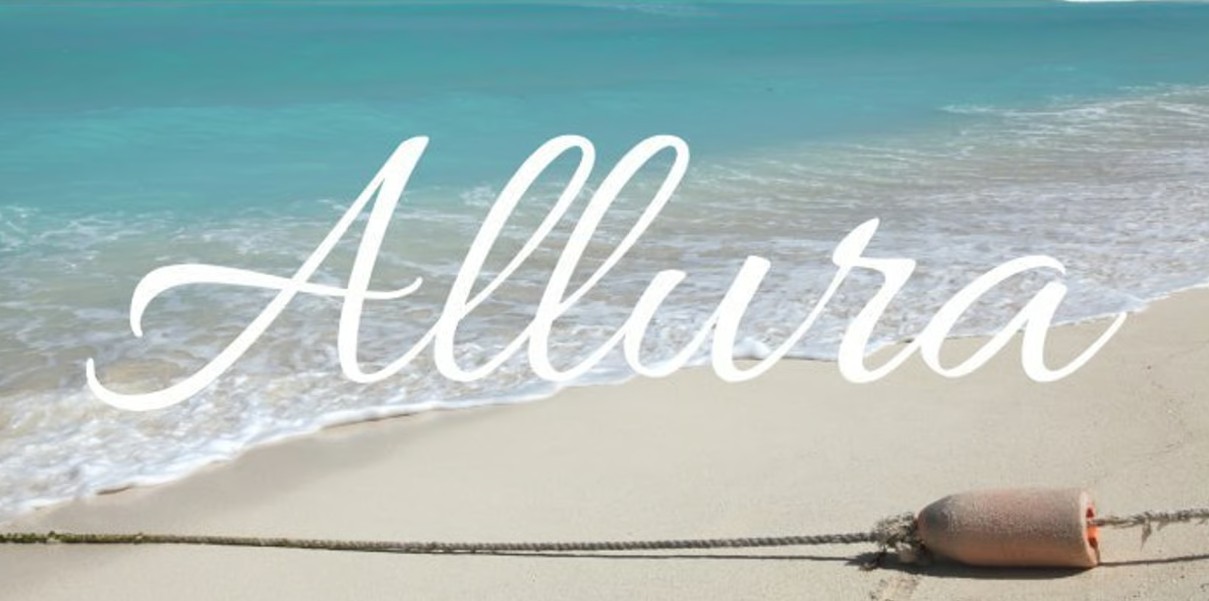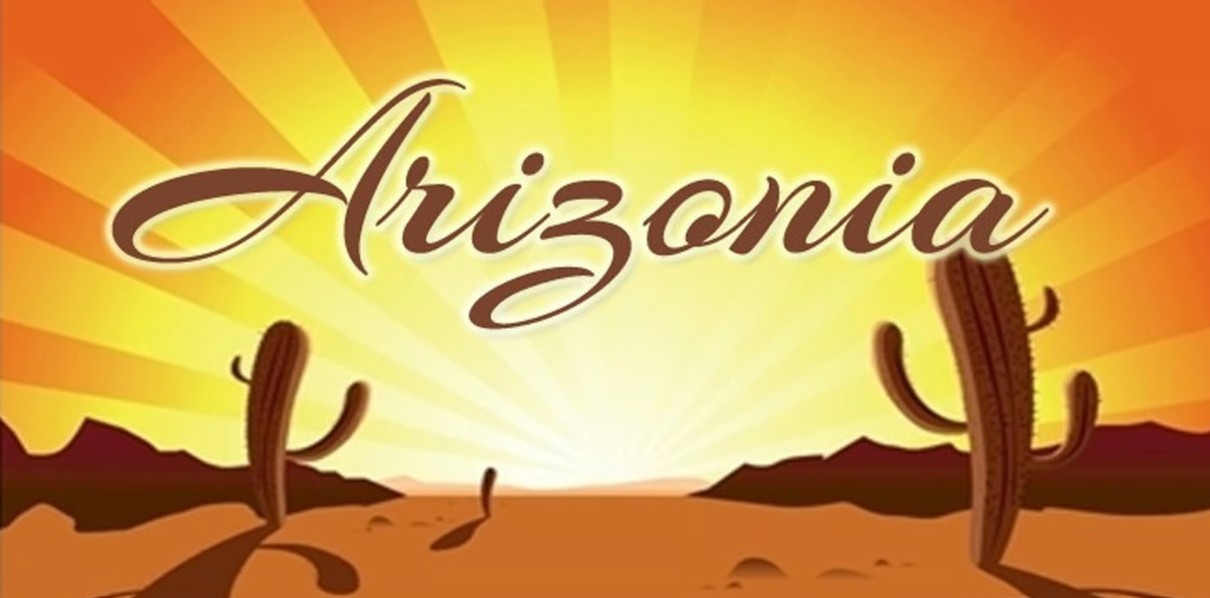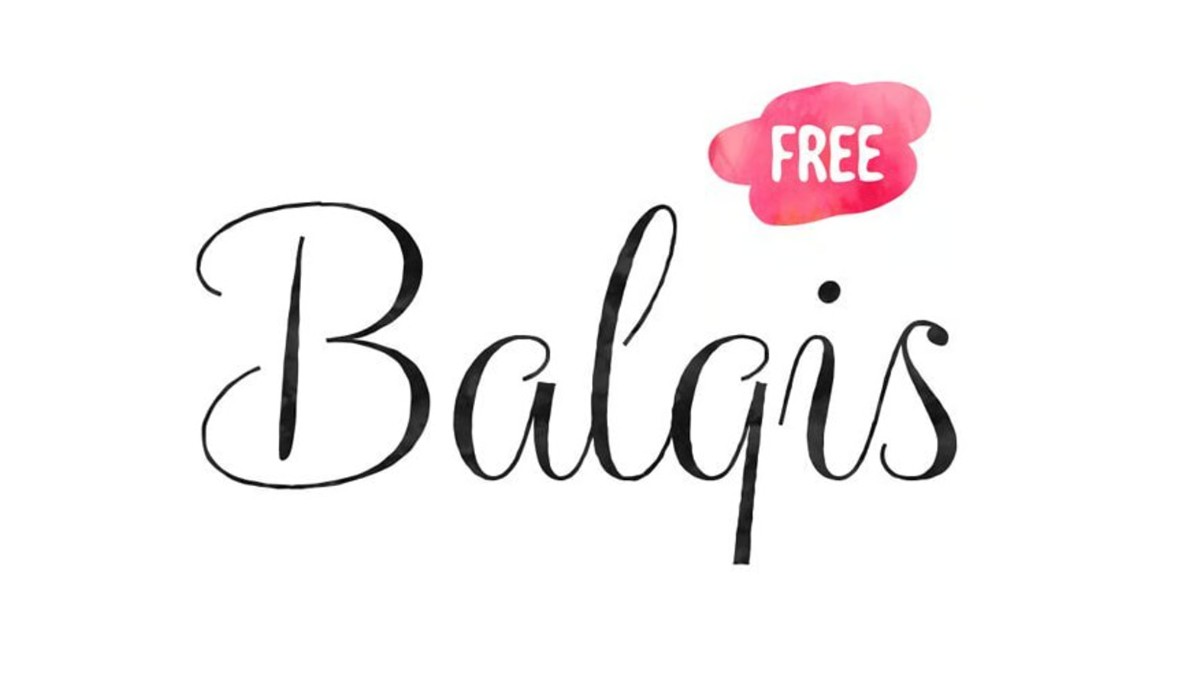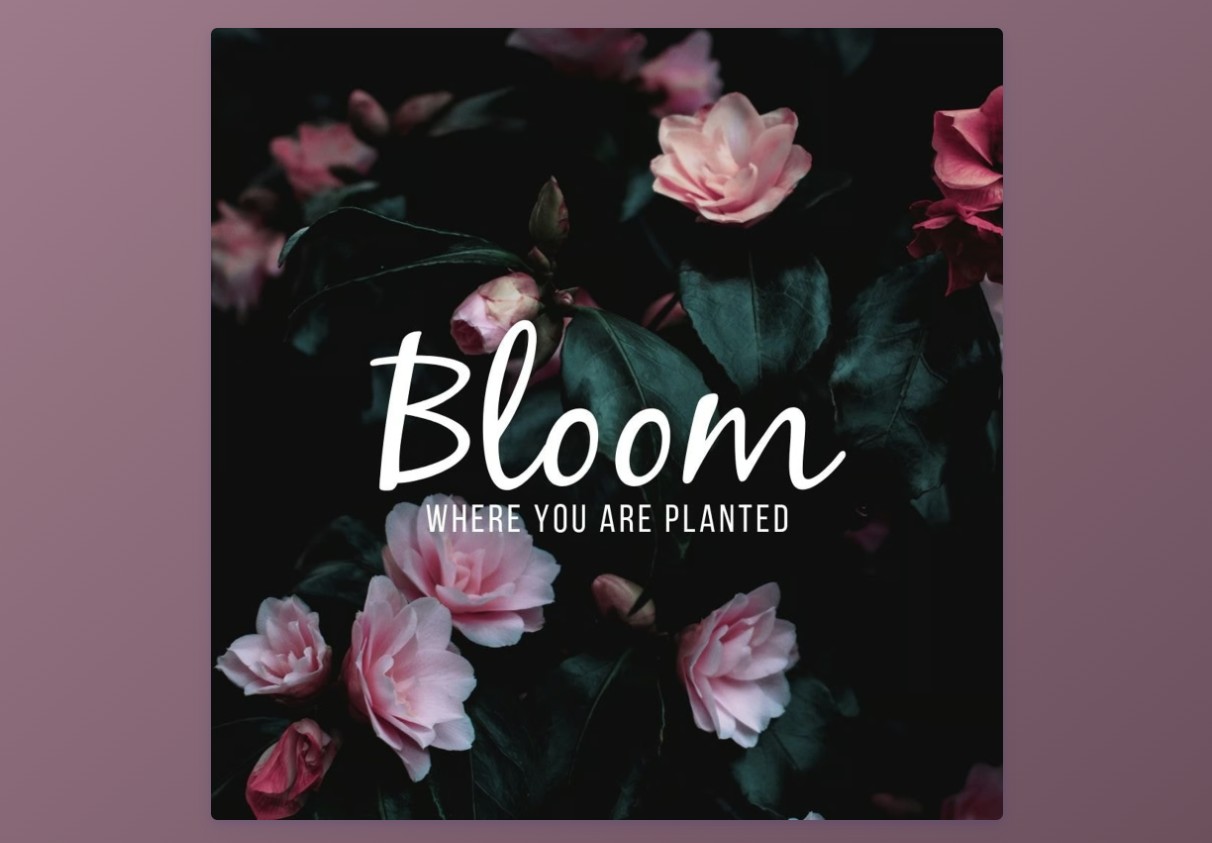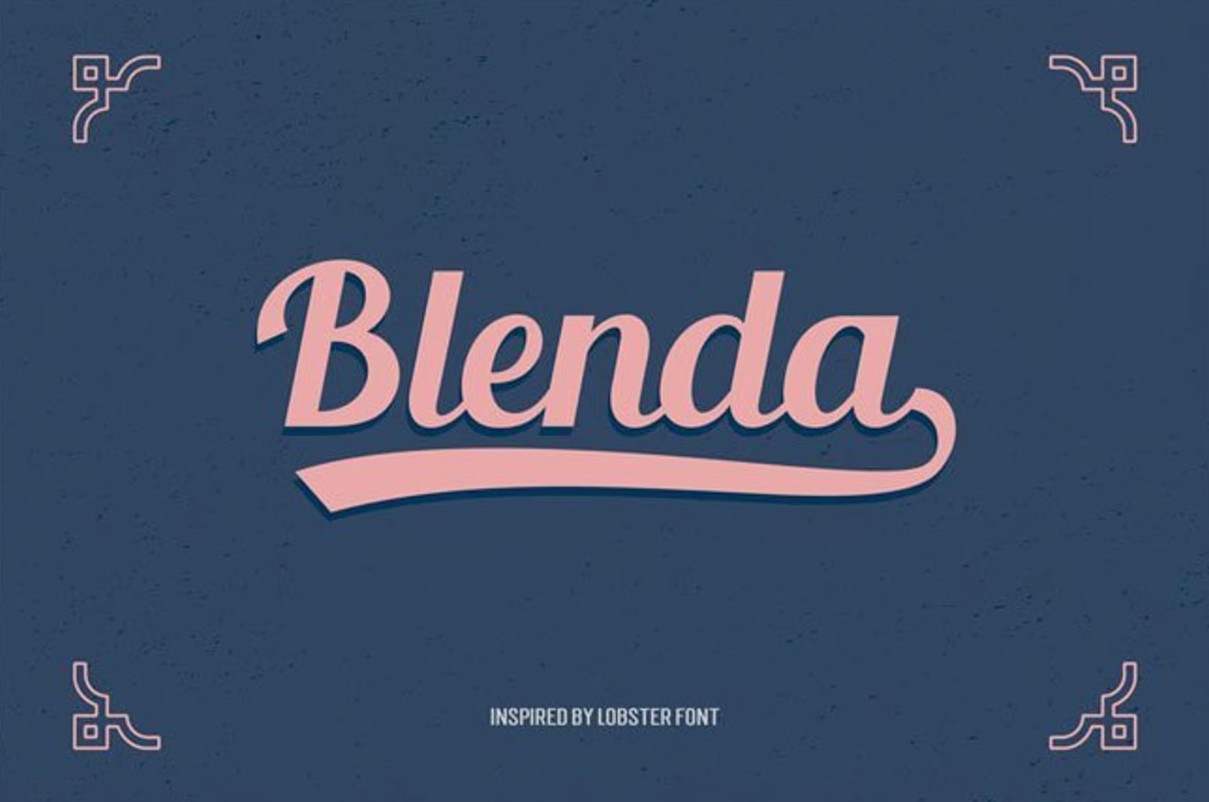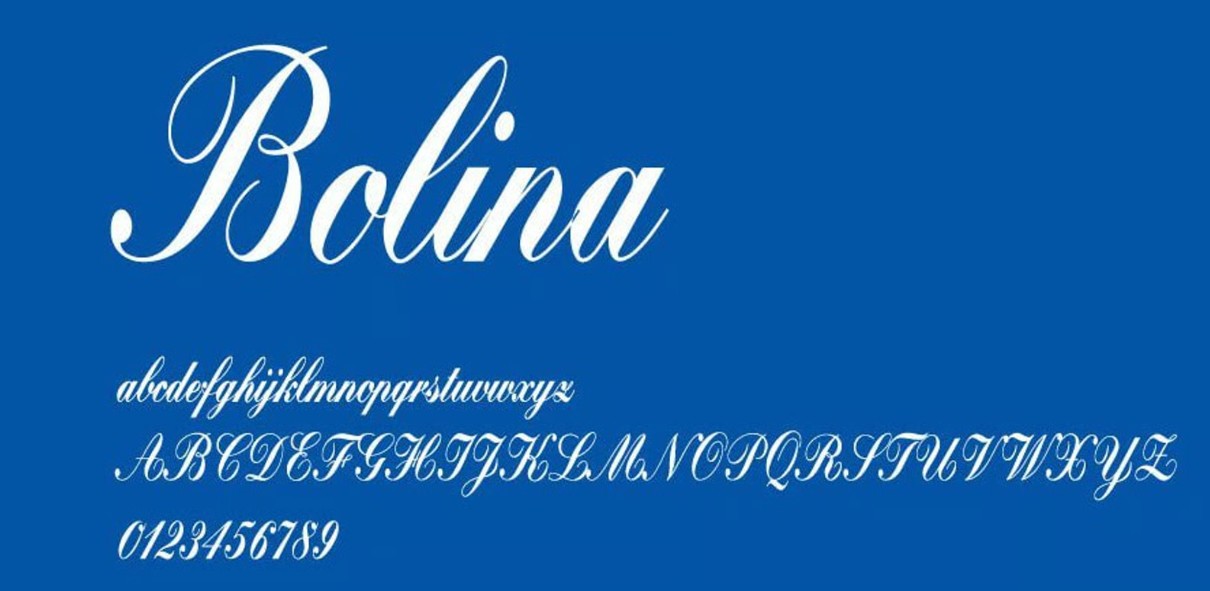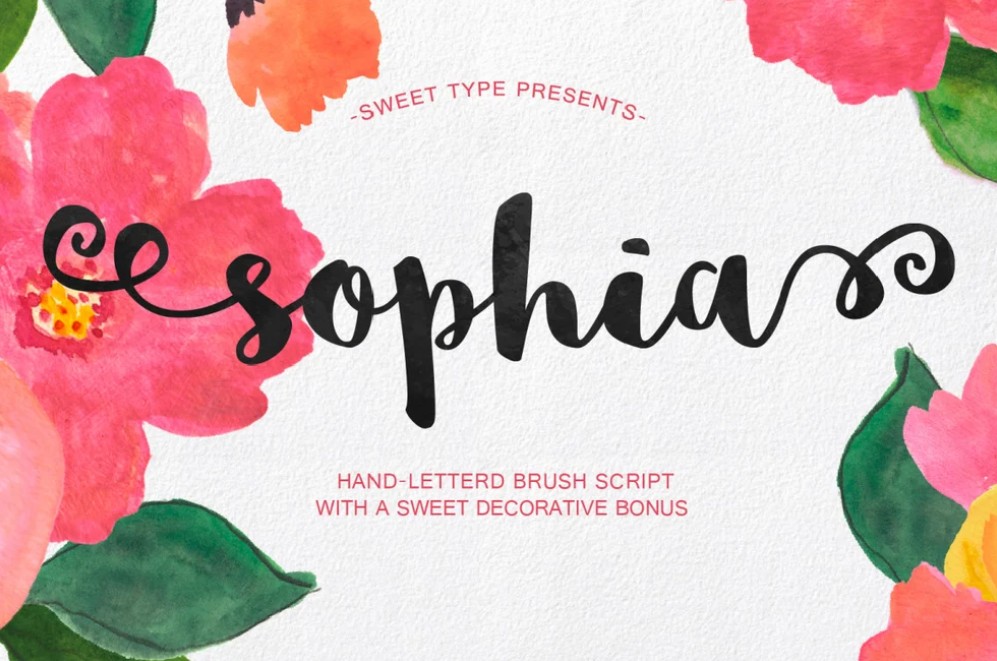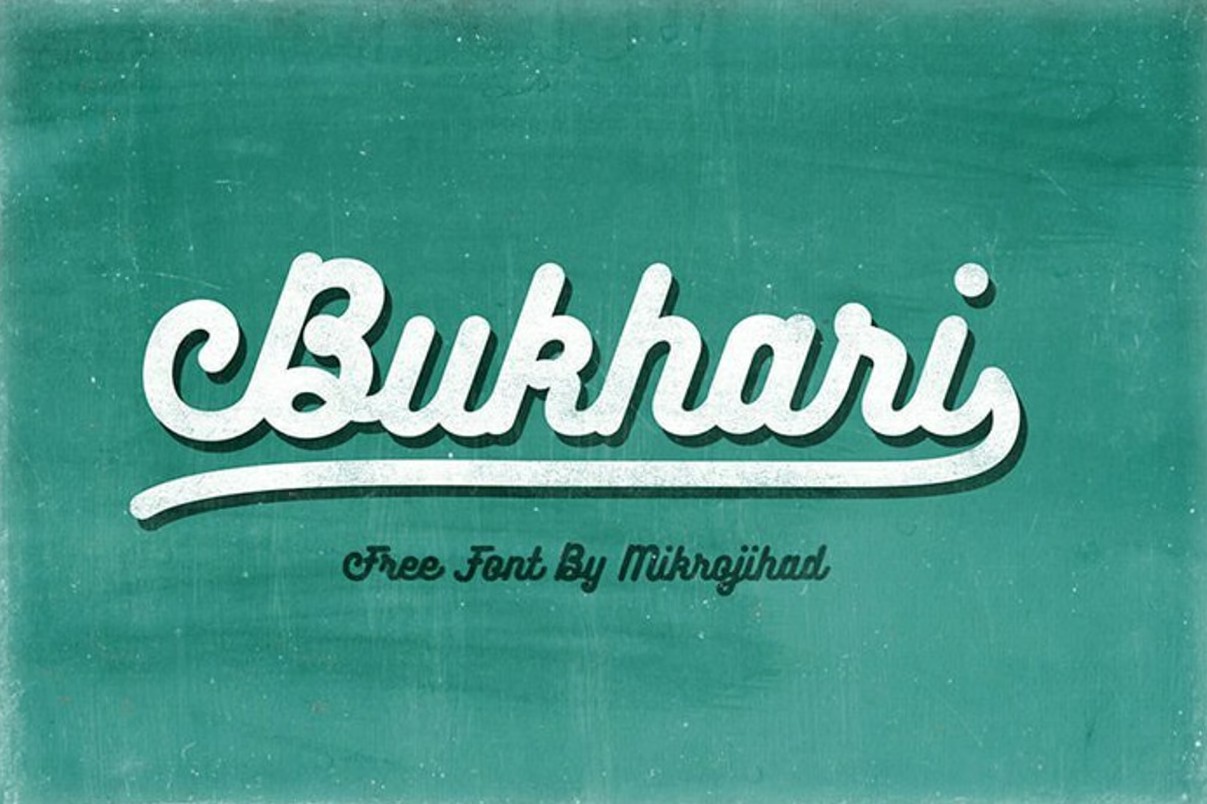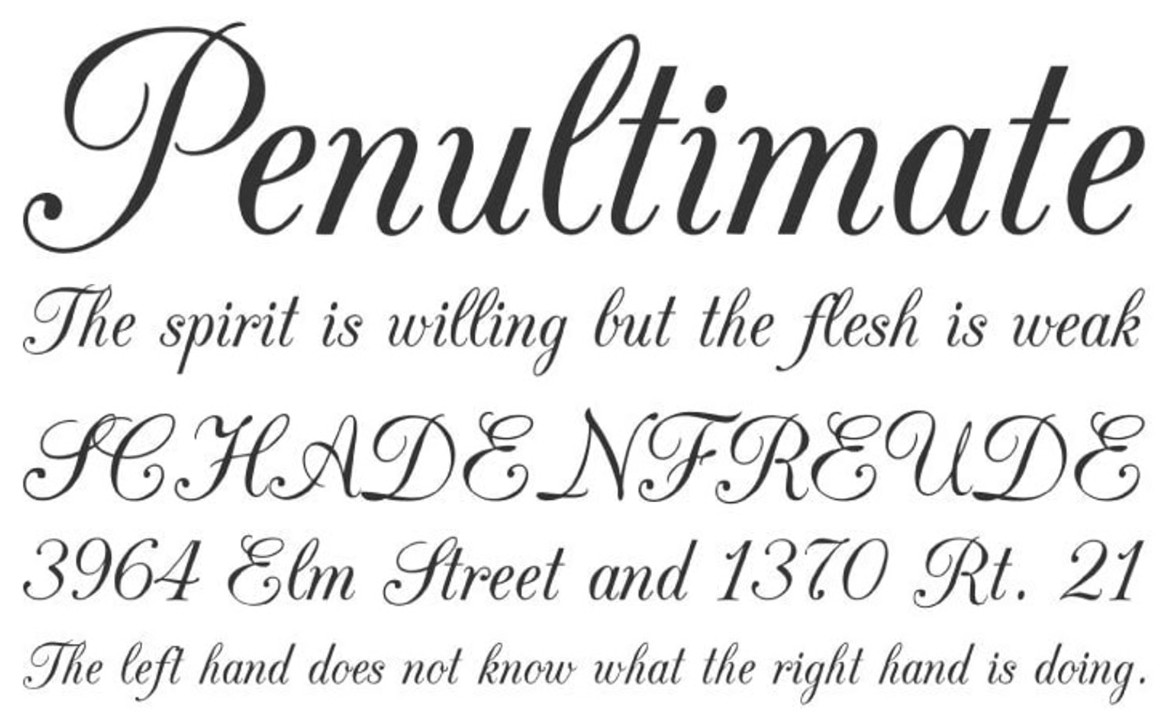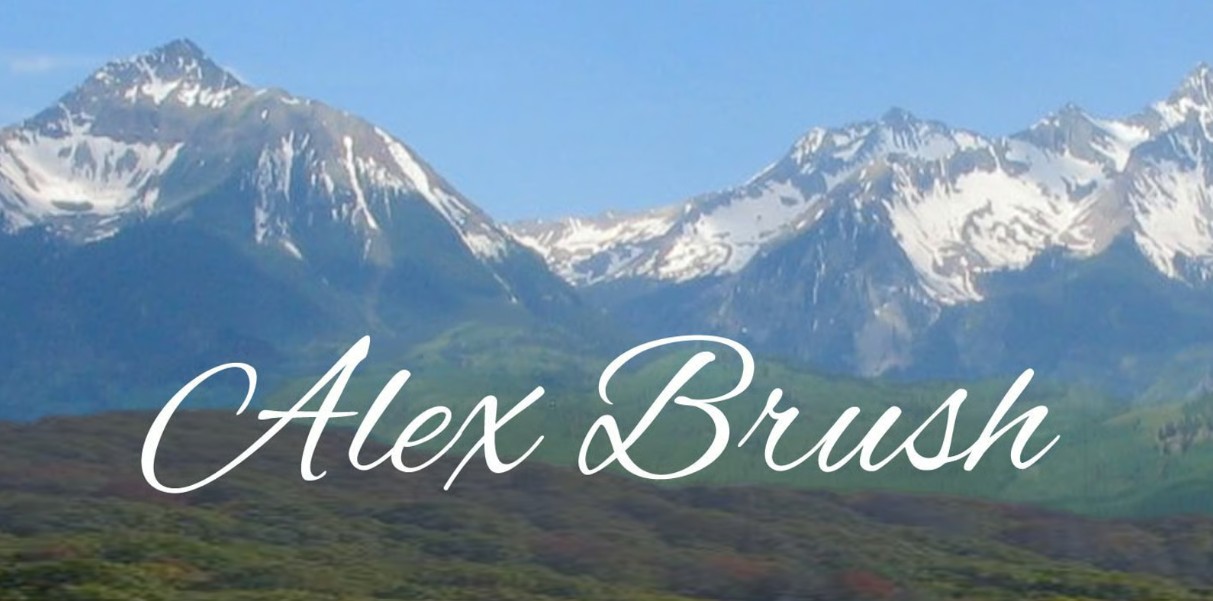
Top 10 font chữ viết tay đẹp miễn phí
Font chữ viết tay luôn là lựa chọn được nhiều nhà thiết kế yêu thích nhờ khả năng tạo cảm giác tự nhiên, cá nhân và giàu cảm xúc.
Top 10 font chữ viết tay đẹp miễn phí
Phông chữ viết tay (handwritten font) luôn là một trong những lựa chọn được yêu thích trong thiết kế đồ họa nhờ khả năng tạo cảm giác gần gũi, cá nhân và giàu cảm xúc. Khác với các kiểu chữ máy tính truyền thống, font chữ viết tay mô phỏng nét chữ tự nhiên của con người, mang đến sự mềm mại, độc đáo và giúp các sản phẩm thiết kế trở nên nổi bật hơn.
Trong nhiều lĩnh vực như thiết kế logo, bao bì sản phẩm, thiệp mời, poster, bài đăng mạng xã hội hay nhận diện thương hiệu, phông chữ viết tay thường được sử dụng để tạo điểm nhấn và truyền tải phong cách riêng. Tùy theo đặc điểm từng loại font, người thiết kế có thể lựa chọn kiểu chữ thanh lịch, cổ điển, trẻ trung hoặc cá tính.
Hiện nay có rất nhiều phông chữ viết tay miễn phí được chia sẻ dành cho mục đích cá nhân và một số dự án thương mại. Trong đó, 10 font chữ như Alex Brush, Allura Regular, Arizonia, Balqis, Black Jack, Blenda, Bolina, Sophia, Bukhari Script và CAC Champagne là những lựa chọn nổi bật nhờ thiết kế đẹp mắt, dễ sử dụng và phù hợp với nhiều phong cách sáng tạo khác nhau.
1. Alex Brush
Alex Brush là một phông chữ viết tay mang phong cách thư pháp cổ điển với những nét cọ mềm mại và phần chữ hoa đầy ấn tượng. Đây là kiểu font được thiết kế theo hướng thanh lịch, tạo cảm giác sang trọng nhưng vẫn giữ được sự tự nhiên của nét viết tay.
Điểm đặc biệt của Alex Brush nằm ở phần nét chữ không quá dài ở các ký tự lên cao và xuống thấp như nhiều font thư pháp khác. Điều này giúp font trở nên dễ đọc hơn, ngay cả khi được sử dụng trong các đoạn chữ dài hoặc kích thước nhỏ.
Với vẻ đẹp cổ điển và khả năng hiển thị rõ ràng, Alex Brush phù hợp cho nhiều thiết kế như logo thương hiệu cao cấp, thiệp cưới, tiêu đề sách, poster nghệ thuật hoặc các sản phẩm yêu cầu sự tinh tế. Đây là một lựa chọn lý tưởng dành cho những ai muốn tạo cảm giác sang trọng nhưng không quá cầu kỳ.
2. Allura Regular
Allura Regular là một font chữ viết tay mang phong cách nhẹ nhàng, bay bổng với cảm giác tự nhiên giống như nét chữ được viết bằng tay. Font này nổi bật bởi các đường cong mềm mại, tạo nên vẻ đẹp nữ tính và thanh lịch.
Không giống nhiều font thư pháp phức tạp, Allura Regular có thiết kế đơn giản, dễ đọc và có tính ứng dụng cao. Nhờ sự cân bằng giữa nét trang trí và khả năng hiển thị, font chữ này có thể sử dụng trong nhiều loại dự án khác nhau.
Allura Regular đặc biệt phù hợp với thiết kế bao bì sản phẩm, thương hiệu mỹ phẩm, thiệp chúc mừng, logo cá nhân hoặc các nội dung cần tạo cảm giác thân thiện. Sự linh hoạt của font giúp nó trở thành một trong những lựa chọn phổ biến trong nhóm font viết tay miễn phí.
3. Arizonia
Arizonia là một phông chữ viết tay gây chú ý nhờ sự kết hợp giữa các nét đậm và nét mảnh thay đổi linh hoạt. Sự tương phản này tạo nên cảm giác chuyển động, giúp chữ viết trở nên nổi bật và có chiều sâu hơn.
Font Arizonia sở hữu nhiều ký tự đặc biệt, trong đó một số chữ thường như ký tự “z” được thiết kế rất độc đáo. Ngoài ra, font còn mang một chút ảnh hưởng từ phong cách chữ Ả Rập, tạo nên nét riêng biệt so với các font thư pháp thông thường.
Với vẻ ngoài cá tính và giàu tính nghệ thuật, Arizonia thích hợp cho tiêu đề lớn, poster, thiết kế thời trang, bìa album hoặc các dự án cần tạo ấn tượng mạnh ngay từ cái nhìn đầu tiên.
4. Balqis
Balqis là font chữ viết tay hiện đại với phong cách đơn giản, nhẹ nhàng và gần gũi. Đây là lựa chọn phù hợp khi người thiết kế muốn thêm yếu tố cá nhân vào sản phẩm nhưng không muốn tạo cảm giác quá trang trọng hoặc cầu kỳ.
Điểm nổi bật của Balqis nằm ở sự thay đổi giữa nét dày và nét mỏng, giúp từng ký tự có chiều sâu và thể hiện rõ nét đặc trưng của chữ viết tay thật. Font mang đến cảm giác tự nhiên, giống như một dòng chữ được ghi bằng bút trên giấy.
Balqis phù hợp với các thiết kế như nhật ký cá nhân, blog, thiệp, bao bì thủ công, thương hiệu thời trang hoặc các sản phẩm hướng đến sự tinh tế và gần gũi.
5. Black Jack
Black Jack là một font chữ viết tay hiện đại với kiểu nét liền mạch (monoline), tạo cảm giác sạch sẽ, đơn giản và dễ sử dụng. Không quá cầu kỳ như những font thư pháp truyền thống, Black Jack tập trung vào sự tự nhiên và khả năng ứng dụng rộng rãi.
Nhờ thiết kế cân bằng, font này phù hợp cho cả phong cách nữ tính lẫn nam tính. Đây là điểm khác biệt giúp Black Jack trở thành lựa chọn linh hoạt trong nhiều lĩnh vực thiết kế.
Font Black Jack có thể được sử dụng trong logo, tiêu đề, quảng cáo, thiết kế thương hiệu hoặc các sản phẩm cần một kiểu chữ viết tay hiện đại nhưng không quá phô trương.
6. Blenda
Blenda là một font chữ viết tay lấy cảm hứng từ phong cách cổ điển với thiết kế dày, vui nhộn và giàu cá tính. So với những font chữ mềm mại truyền thống, Blenda tạo cảm giác mạnh mẽ hơn nhờ các đường nét lớn và rõ ràng.